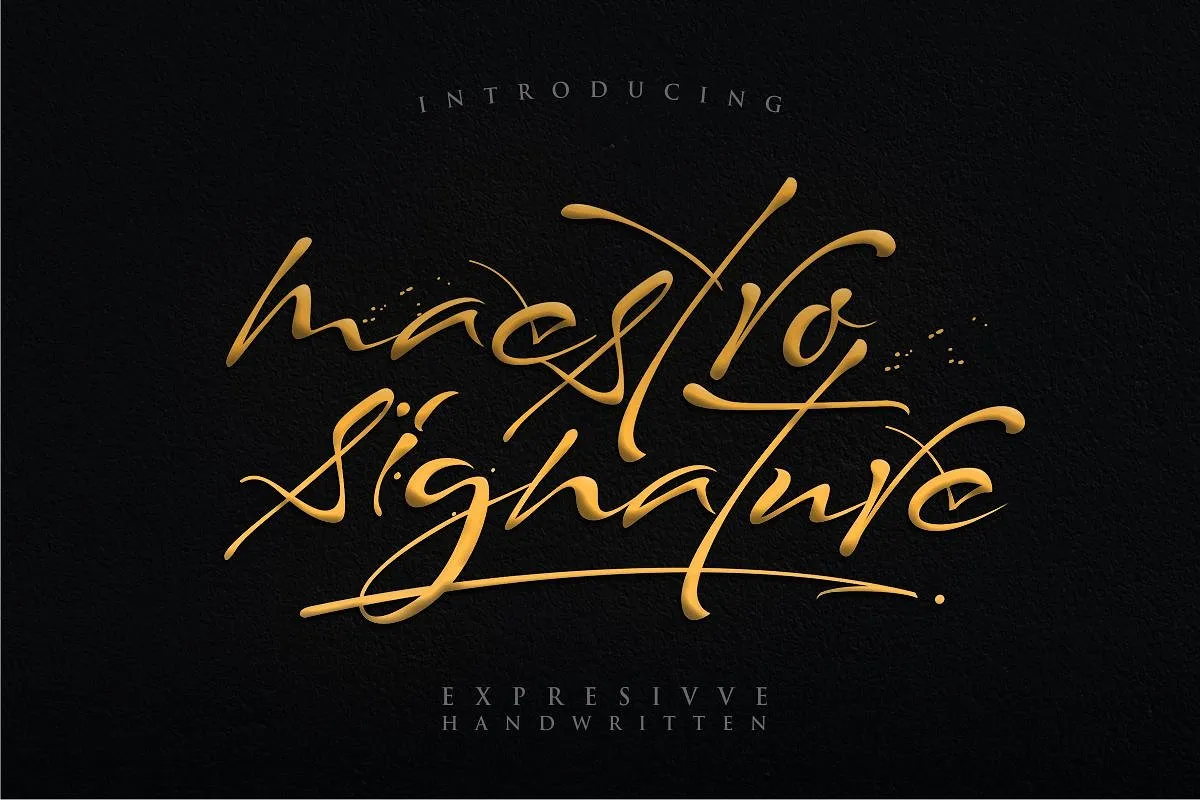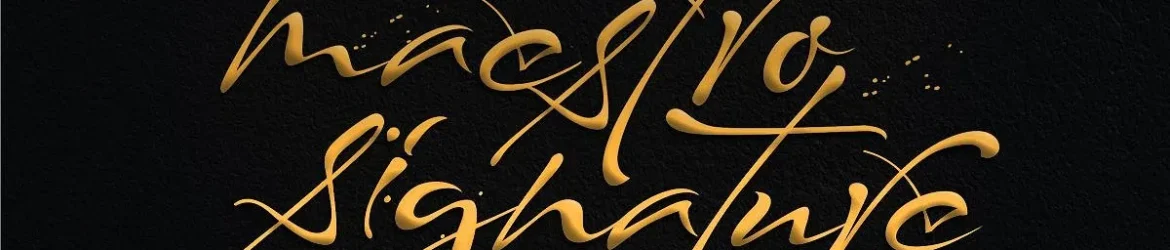
Maestro Signature Font – Download Grátis
Aqui está uma versão para o português do Brasil das descrições solicitadas: Bem-vindo! A nossa fonte Maestro Signature é um belo exemplar de uma nova fonte script chamada Calligrafia Moderna, criado por Hamilton através da sua própria escrita. Esta fonte apresenta formas modernas e únicas na arte da escrita chinesa, mantendo a naturalidade no seu estilo. Combinando o charme e sofisticação de uma fonte de alto padrão com um toque único e inovador, esta é uma opção perfeita para fazer mensagens em citações, assinaturas, logotipos, gráficos de evento casamento ou qualquer outro tipo de arte que você possa imaginar. Sempre clássico e distinto, esta fonte oferece um toque moderno e luxuoso aos seus designs. Através da sua capacidade de criar uma atmosfera única em cada design, a Maestro Signature Font torna-se não apenas uma ferramenta prática no seu trabalho diário, mas também uma peça chave para o estilo distintivo que você deseja transmitir. Esta font é ideal tanto para os amantes de design e criativos quanto para aqueles que desejam adicionar um toque único a seus trabalhos gráficos.